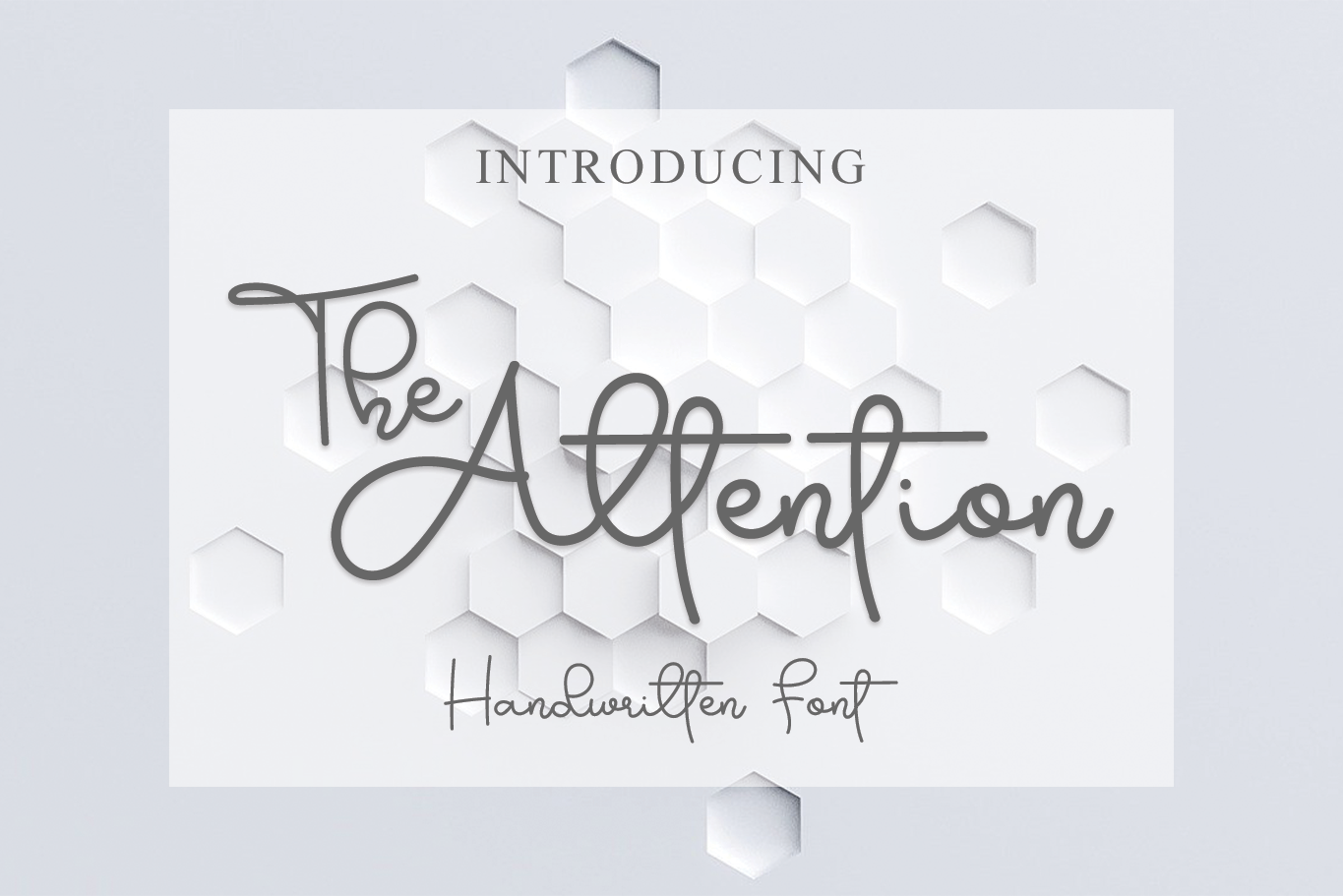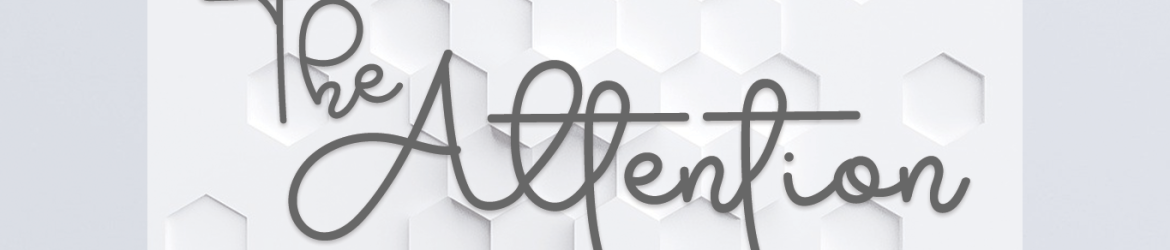
The Attention Font – Download Grátis
A fonte ‘The Attention Font’ é uma elegante caligrafia delicada que transpira sofisticação e classe. É especialmente concebida para aqueles que buscam um visual agradável e renovador em suas criações gráficas. Seja ela usada em cartões de visita, letras do site ou qualquer outro material digital, ‘The Attention Font’ garante um ar refinado e moderno. Este conjunto de caracteres não apenas oferece uma aparência sofisticada, mas também traz uma sensação acolhedora e natural que pode enriquecer qualquer projeto visual. Inspirada na caligrafia manuscrita, a fonte é perfeita para quem busca um toque pessoal em seus materiais digitais. É uma escolha inteligente para designers buscando criar um arco-íris de experiências visuais que chamem a atenção e mantenham os olhos da sua audiência presos ao trabalho.